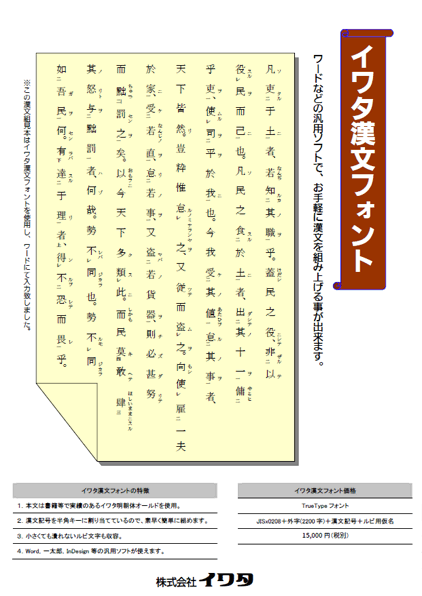
イワタ漢文フォントは漢文を入力するためのフォントです。
文字デザインは定評のあるイワタ明朝体オールドをベースにしています。さらに漢文記号を半角英数字のキーに割り当てているので、美しい漢文を速く・簡単に入力することができます。
- 本文は書籍等で実績のあるイワタ明朝体オールドを使用。
- 小さくても潰れないルビ文字も収容。